今回紹介するのはV字の赤入れです。V字は書き込む位置や向きで様々な指示ができます。
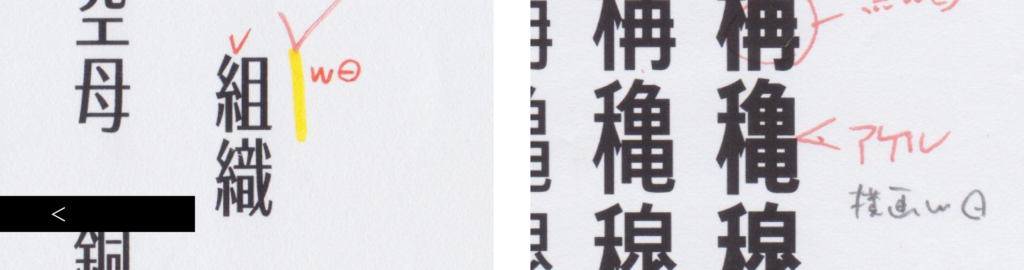
要素同士のあいだに書き込まれる1つのV字は「あいだが狭くなっているから、空ける」という指示です。横向きでも縦向きでも使えて、縦向きは上図の「組」のように偏と旁の間に書かれたりします。「穐」は横画を細くしてあいだを空けるといいよ、と先輩からアドバイスをもらったのでメモがしてあります。
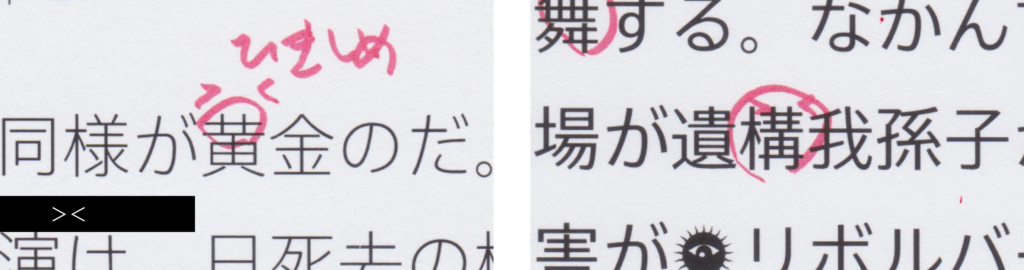
向かい合った2つのV字は「幅を引き締める」の意味で、逆に幅を広くしたい場合は逆向き<>で書き込みます。「黄」は上の部分だけ横に引き締めるという指示です。「構」は旁の上部分だけへの指示なのか、旁全体への指示なのか……判断に迷った時はチェックした人に聞きます。